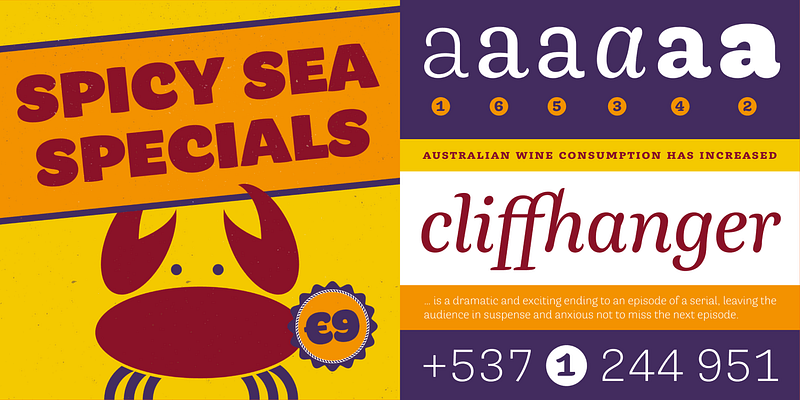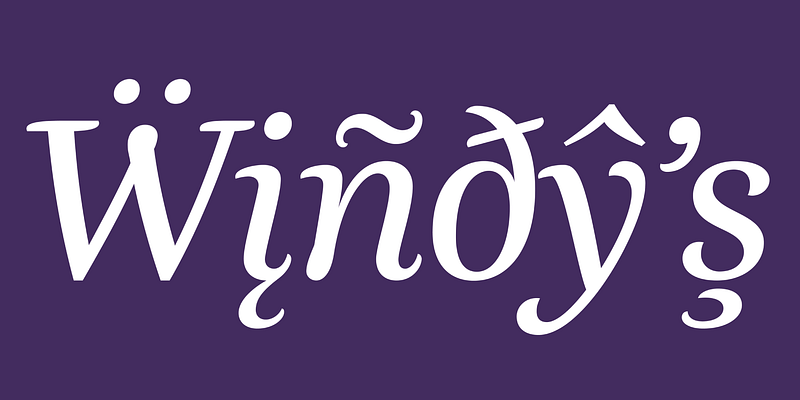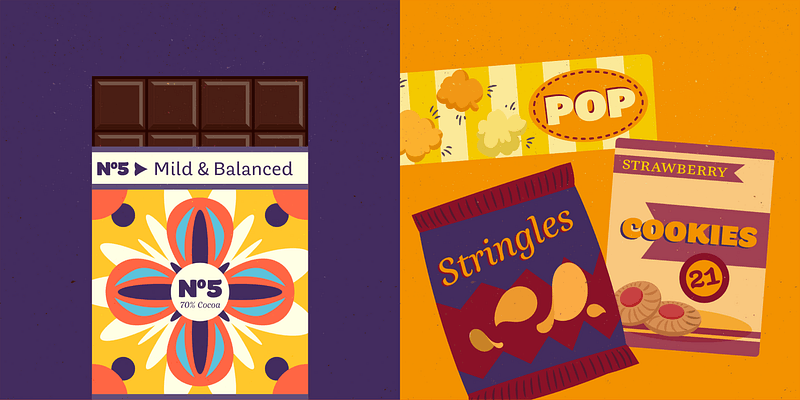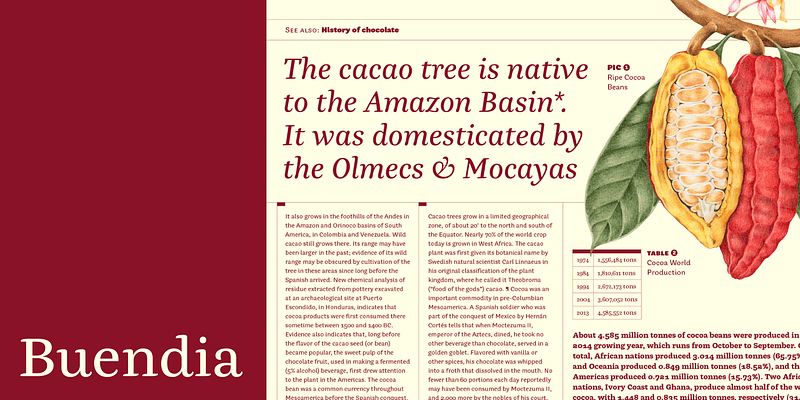
César Puertas lädt Sie dazu ein, die Bedeutung einer Schriftfamilie neu zu überdenken. Buendia verhält sich wie eine echte Familie: Anstatt einen Satz von Buchstabenformen mit mehr oder weniger Gewicht zu versehen, ist jedes Familienmitglied eine andere Person. Aufbauend auf einem einzigen Skelett bietet die Schriftfamilie Designvarianten aus verschiedenen Schriftklassen. Eine Light und Medium Neo-Grotesque gehen in eine kalligrafische Serifenschrift in Regular und Italic über, bevor sie sich in eine bürstenartige Bold Slab Serif und schließlich in eine pummelige ExtraBold Sans Serif verwandeln. Abgerundete Buchstabenformen, geschwungene Enden, blattförmige Serifen und Endungen sowie sanft gewölbte Strichabschlüsse verleihen der lässigen Schrift ein einladendes, freundliches Auftreten. Bold Monday, 2015.